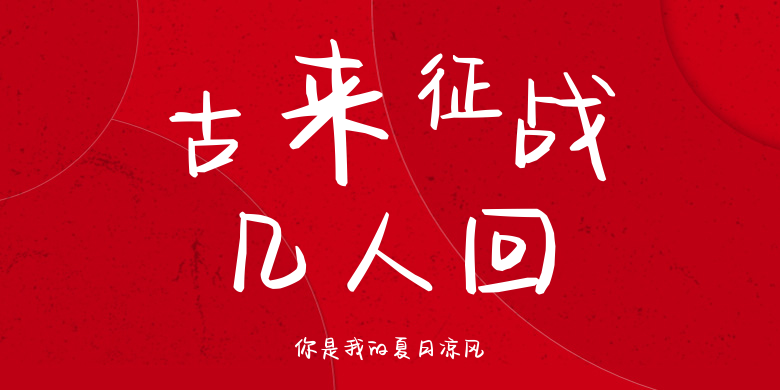
你是我的夏日凉风
你是我的夏日凉风,这款字体结构工整、笔画清晰,兼顾美观与易读性,适用于标题、正文、海报、包装、LOGO 等多种场景。字形优雅稳定,风格百搭耐看,适配日常排版与创意设计,让文字呈现更舒适、更具质感。你是我的夏日凉风一笔一画,皆是细节,以均衡的比例、流畅的线条打造舒适视觉体验,字形端正大气,风格简约现代。无论是商业设计、品牌宣传还是日常排版,都能轻松驾驭,让文字更有格调与力量。你是我的夏日凉风字体下载。